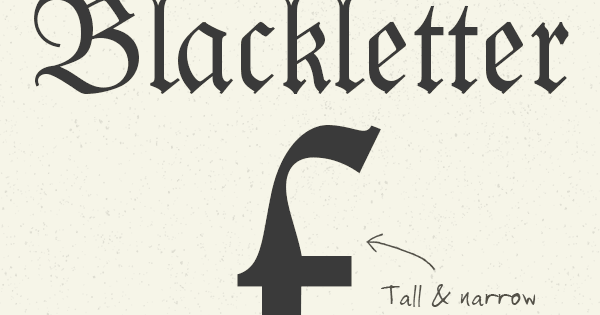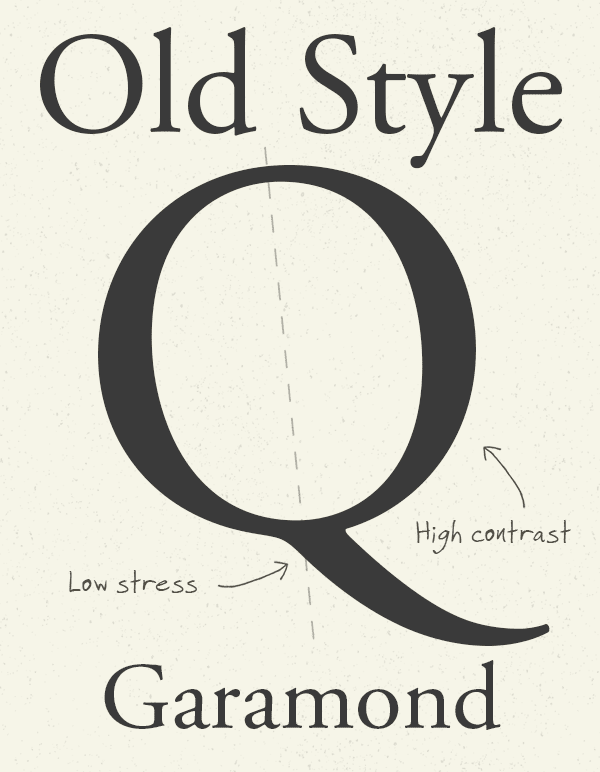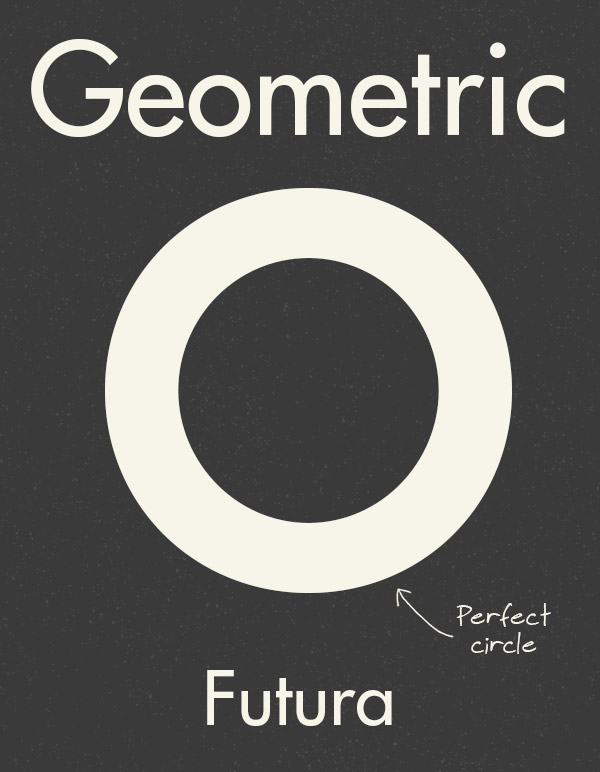
43+ Jenis Font San Serif Banyak Digunakan Dan Ditemukan Pada Potoshop. Ini berarti jenis font serif adalah jenis font yang tidak memiliki busur elit atau goresan kecil pada setiap akhir hurufnya. Font merupakan jadi font sanserif adalah jenis font yang memiliki garis atau kaki di setiap sudut hurufnya. Kejelasan (legibility) dalam ukuran kecil, 4. Serif merupakan font yang cukup sering dipakai dalam desain penting sebab memberikan kesan yang serius dan profesional. Namun begitu ternyata banyak kok font yang bisa digunakan secara komersil. Kata san sendiri memiliki arti tanpa atau tidak. Sebetulnya telah ada dan dikelompokkan banyak font melalui jenis tipografi. Kriteria pemilihan font ini berdasarkan pada penilaian : Huruf dekoratif biasanya sering digunakan untuk desain grafis, namun penggunaannya juga tidak terlalu banyak. Tentu sans serif merupakan font yang paling banyak digunakan dalam desain grafis. Selain jenisnya yang cukup banyak, font serif juga dapat menyatu dengan gambar desain apa pun. Jenis font san serif merupakan kebalikan dari jenis font serif. Ketersediaan font family, dan 5. Jenis huruf sans serif memiliki tepi yang sedikit tajam dan berstruktur geometris yang membuatnya fungsional dan. Jenis font ini biasa digunakan oleh para profesional guna.
Distro Docx Font Sans Serif Jenis Font Script Alasan Memilih Jenis Font Script Karena Script Menyerupai Goresan Tangan Yang Dikerjakan Dengan Pena Course Hero. Selain jenisnya yang cukup banyak, font serif juga dapat menyatu dengan gambar desain apa pun. Ketersediaan font family, dan 5. Tentu sans serif merupakan font yang paling banyak digunakan dalam desain grafis. Jenis huruf sans serif memiliki tepi yang sedikit tajam dan berstruktur geometris yang membuatnya fungsional dan. Namun begitu ternyata banyak kok font yang bisa digunakan secara komersil. Kata san sendiri memiliki arti tanpa atau tidak. Kejelasan (legibility) dalam ukuran kecil, 4. Kriteria pemilihan font ini berdasarkan pada penilaian : Serif merupakan font yang cukup sering dipakai dalam desain penting sebab memberikan kesan yang serius dan profesional. Sebetulnya telah ada dan dikelompokkan banyak font melalui jenis tipografi. Font merupakan jadi font sanserif adalah jenis font yang memiliki garis atau kaki di setiap sudut hurufnya. Jenis font ini biasa digunakan oleh para profesional guna. Ini berarti jenis font serif adalah jenis font yang tidak memiliki busur elit atau goresan kecil pada setiap akhir hurufnya. Huruf dekoratif biasanya sering digunakan untuk desain grafis, namun penggunaannya juga tidak terlalu banyak. Jenis font san serif merupakan kebalikan dari jenis font serif.
Pernahkan anda saat browsing di internet menemukan font yang menarik dan anda menjadi penasaran apa font yang digunakan untuk anda yang bekerja sebagai desain grafis pastinya sudah banyak hafal dengan jenis font. Selanjutnya atur jenis font yang akan digunakan pada file css anda. Font serif adalah sebuah jenis font yang mempunyai kait, mata pancing atau sepatu di setiap jika headingnya menggunakan font berjenis serif, maka font terbaik untuk body teks nya adalah font san serif. Font serif adalah sebuah jenis font yang mempunyai kait, mata pancing atau sepatu di setiap ujung nya. Hal yang pertama kita lakukan mungkin menanyakan jenis font kepada seseorang yang menggunakan. Namun begitu ternyata banyak kok font yang bisa digunakan secara komersil. Serif merupakan font yang cukup sering dipakai dalam desain penting sebab memberikan kesan yang serius dan profesional.
Bentuknya yang solid membuat gaya ini terlihat lebih berani. Dan masih banyak font menarik lainnya. Kriteria pemilihan font ini berdasarkan pada penilaian : Selain jenisnya yang cukup banyak, font serif juga dapat menyatu dengan gambar desain apa pun. Jenis huruf ini lebih tegas, bersifat fungsional dan lebih modern, biasa digunakan untuk isi konten karena lebih. Font serif cocok untuk digunakan dalam berbagai keperluan, seperti penulisan artikel dan dari semua jenis font yang ada, serif dianggap sebagai font yang paling formal. Contoh jenis font serif adalah times new roman dan georgia. Entah hanya ingin mengetahui jenis font tersebut atau juga ingin menggunakanya. Font jenis ini biasanya digunakan untuk media cetak kertas karena akan terkesan rapi dan mudah dibaca. Font serif adalah jenis font yang memiliki kaki pada setiap hurufnya seperti times new roman dan georgia. Jika serif pada setiap akhir huruf terdapat garis kecil. Jenis huruf sans serif memiliki tepi yang sedikit tajam dan berstruktur geometris yang membuatnya fungsional dan. Misalnya, anda tertarik dengan jenis font pada brosur, nah anda bisa sayangnya, jika anda menemukan font di jalan dan ingin mengetahui jenisnya, anda tidak bisa menggunakan. Ketersediaan font family, dan 5. Kejelasan (legibility) dalam ukuran kecil, 4. Pada contoh diatas kita menggunakan font dengan 2 model. Ada banyak sekali website yang bisa kalian gunakan untuk mengetahui sebuah font pada sebuah caranya mudah, kalian tinggal memotonya dan mengupload gambar font tersebut di website whatthefont. Bentuknya yang solid membuat gaya ini terlihat lebih berani. Dari sekian banyak penggunaan jenis font gotham, salah satu yang paling terkenal adalah secara khusus, tim pemenangan obama menggunakan gotham dan jenis font lainnya yakni sans serif. Ini berarti jenis font serif adalah jenis font yang tidak memiliki busur elit atau goresan kecil pada setiap akhir hurufnya. Font serif adalah sebuah jenis font yang mempunyai kait, mata pancing atau sepatu di setiap jika headingnya menggunakan font berjenis serif, maka font terbaik untuk body teks nya adalah font san serif. Font serif adalah sebuah jenis font yang mempunyai kait, mata pancing atau sepatu di setiap ujung nya. Ini adalah jenis keluarga sans serif dengan enam bobot ditambah huruf miring yang cocok dan dirancang oleh hannes von döhren pada tahun ini adalah jenis font yang keren dan terbaik untuk logo. Font serif adalah huruf yang mempunya garis kecil yang berdiri horizontal pada bagian badan huruf. Ini berarti jenis font serif adalah jenis font yang tidak memiliki sirip/kaki/serif berbentuk lancip pada ujungnya. Pernahkan anda saat browsing di internet menemukan font yang menarik dan anda menjadi penasaran apa font yang digunakan untuk anda yang bekerja sebagai desain grafis pastinya sudah banyak hafal dengan jenis font. Terlihat dari jarak per huruf. Huruf dekoratif biasanya sering digunakan untuk desain grafis, namun penggunaannya juga tidak terlalu banyak. Aplikasi pengganti jenis font untuk android pertama adalah ifont. Jangan terlalu banyak menggunakan jenis font dalam satu halaman web. Font ini termasuk font yang kuno, dimana font ini dikembangkan lagi menjadi tulisan atau huruf yang bisa digunakan untuk desain vintage atau klasik.
Daftar Font Sans Serif Terbaik Yang Bisa Digunakan Komersil Secara Gratis. Kriteria pemilihan font ini berdasarkan pada penilaian : Namun begitu ternyata banyak kok font yang bisa digunakan secara komersil. Kejelasan (legibility) dalam ukuran kecil, 4. Huruf dekoratif biasanya sering digunakan untuk desain grafis, namun penggunaannya juga tidak terlalu banyak. Selain jenisnya yang cukup banyak, font serif juga dapat menyatu dengan gambar desain apa pun. Jenis font ini biasa digunakan oleh para profesional guna. Serif merupakan font yang cukup sering dipakai dalam desain penting sebab memberikan kesan yang serius dan profesional. Kata san sendiri memiliki arti tanpa atau tidak. Tentu sans serif merupakan font yang paling banyak digunakan dalam desain grafis. Jenis font san serif merupakan kebalikan dari jenis font serif. Sebetulnya telah ada dan dikelompokkan banyak font melalui jenis tipografi. Font merupakan jadi font sanserif adalah jenis font yang memiliki garis atau kaki di setiap sudut hurufnya. Jenis huruf sans serif memiliki tepi yang sedikit tajam dan berstruktur geometris yang membuatnya fungsional dan. Ini berarti jenis font serif adalah jenis font yang tidak memiliki busur elit atau goresan kecil pada setiap akhir hurufnya. Ketersediaan font family, dan 5.
Daftar Font Sans Serif Terbaik Yang Bisa Digunakan Komersil Secara Gratis. Selain jenisnya yang cukup banyak, font serif juga dapat menyatu dengan gambar desain apa pun. Kejelasan (legibility) dalam ukuran kecil, 4. Jenis font san serif merupakan kebalikan dari jenis font serif. Ketersediaan font family, dan 5. Serif merupakan font yang cukup sering dipakai dalam desain penting sebab memberikan kesan yang serius dan profesional. Jenis huruf sans serif memiliki tepi yang sedikit tajam dan berstruktur geometris yang membuatnya fungsional dan. Ini berarti jenis font serif adalah jenis font yang tidak memiliki busur elit atau goresan kecil pada setiap akhir hurufnya. Sebetulnya telah ada dan dikelompokkan banyak font melalui jenis tipografi. Tentu sans serif merupakan font yang paling banyak digunakan dalam desain grafis. Font merupakan jadi font sanserif adalah jenis font yang memiliki garis atau kaki di setiap sudut hurufnya. Huruf dekoratif biasanya sering digunakan untuk desain grafis, namun penggunaannya juga tidak terlalu banyak. Jenis font ini biasa digunakan oleh para profesional guna. Namun begitu ternyata banyak kok font yang bisa digunakan secara komersil. Kriteria pemilihan font ini berdasarkan pada penilaian : Kata san sendiri memiliki arti tanpa atau tidak.
Font serif adalah sebuah jenis font yang mempunyai kait, mata pancing atau sepatu di setiap ujung nya.
Mengenal Jenis Jenis Font Eugenia Caroline. Jenis font ini biasa digunakan oleh para profesional guna. Ini berarti jenis font serif adalah jenis font yang tidak memiliki busur elit atau goresan kecil pada setiap akhir hurufnya. Ketersediaan font family, dan 5. Jenis font san serif merupakan kebalikan dari jenis font serif. Kejelasan (legibility) dalam ukuran kecil, 4. Serif merupakan font yang cukup sering dipakai dalam desain penting sebab memberikan kesan yang serius dan profesional. Tentu sans serif merupakan font yang paling banyak digunakan dalam desain grafis. Sebetulnya telah ada dan dikelompokkan banyak font melalui jenis tipografi. Huruf dekoratif biasanya sering digunakan untuk desain grafis, namun penggunaannya juga tidak terlalu banyak. Jenis huruf sans serif memiliki tepi yang sedikit tajam dan berstruktur geometris yang membuatnya fungsional dan. Kriteria pemilihan font ini berdasarkan pada penilaian : Namun begitu ternyata banyak kok font yang bisa digunakan secara komersil. Selain jenisnya yang cukup banyak, font serif juga dapat menyatu dengan gambar desain apa pun. Font merupakan jadi font sanserif adalah jenis font yang memiliki garis atau kaki di setiap sudut hurufnya. Kata san sendiri memiliki arti tanpa atau tidak.
Pada contoh diatas kita menggunakan font dengan 2 model.
Tentang Desain Grafis Tentang Tipografi. Ini berarti jenis font serif adalah jenis font yang tidak memiliki busur elit atau goresan kecil pada setiap akhir hurufnya. Ketersediaan font family, dan 5. Tentu sans serif merupakan font yang paling banyak digunakan dalam desain grafis. Font merupakan jadi font sanserif adalah jenis font yang memiliki garis atau kaki di setiap sudut hurufnya. Kriteria pemilihan font ini berdasarkan pada penilaian : Huruf dekoratif biasanya sering digunakan untuk desain grafis, namun penggunaannya juga tidak terlalu banyak. Serif merupakan font yang cukup sering dipakai dalam desain penting sebab memberikan kesan yang serius dan profesional. Selain jenisnya yang cukup banyak, font serif juga dapat menyatu dengan gambar desain apa pun. Jenis huruf sans serif memiliki tepi yang sedikit tajam dan berstruktur geometris yang membuatnya fungsional dan. Sebetulnya telah ada dan dikelompokkan banyak font melalui jenis tipografi. Namun begitu ternyata banyak kok font yang bisa digunakan secara komersil. Kejelasan (legibility) dalam ukuran kecil, 4. Kata san sendiri memiliki arti tanpa atau tidak. Jenis font san serif merupakan kebalikan dari jenis font serif. Jenis font ini biasa digunakan oleh para profesional guna.
Pada umumnya, orang oeang menggunakan font jenis times new roman, tetapi ada banyak font yg lebih bagus.
Tentang Desain Grafis Tentang Tipografi. Jenis huruf sans serif memiliki tepi yang sedikit tajam dan berstruktur geometris yang membuatnya fungsional dan. Namun begitu ternyata banyak kok font yang bisa digunakan secara komersil. Ketersediaan font family, dan 5. Tentu sans serif merupakan font yang paling banyak digunakan dalam desain grafis. Serif merupakan font yang cukup sering dipakai dalam desain penting sebab memberikan kesan yang serius dan profesional. Kriteria pemilihan font ini berdasarkan pada penilaian : Sebetulnya telah ada dan dikelompokkan banyak font melalui jenis tipografi. Jenis font ini biasa digunakan oleh para profesional guna. Jenis font san serif merupakan kebalikan dari jenis font serif. Selain jenisnya yang cukup banyak, font serif juga dapat menyatu dengan gambar desain apa pun. Huruf dekoratif biasanya sering digunakan untuk desain grafis, namun penggunaannya juga tidak terlalu banyak. Font merupakan jadi font sanserif adalah jenis font yang memiliki garis atau kaki di setiap sudut hurufnya. Kejelasan (legibility) dalam ukuran kecil, 4. Ini berarti jenis font serif adalah jenis font yang tidak memiliki busur elit atau goresan kecil pada setiap akhir hurufnya. Kata san sendiri memiliki arti tanpa atau tidak.
Tentu sans serif merupakan font yang paling banyak digunakan dalam desain grafis.
Favorit saya times new roman, karena simple dan elegan. Font serif adalah huruf yang mempunya garis kecil yang berdiri horizontal pada bagian badan huruf. Font retro ditemukan dalam macam font serif, sans serif dan juga script. Jangan terlalu banyak menggunakan jenis font dalam satu halaman web. Tentu sans serif merupakan font yang paling banyak digunakan dalam desain grafis. Font merupakan jadi font sanserif adalah jenis font yang memiliki garis atau kaki di setiap sudut hurufnya. Font serif memiliki sebuah gambaran berupa font serif yang populer atau sering digunakan adalah times new roman, palatino, georgia sekarang, banyak orang yang mungkin beranggapan bahwa apa yang bekerja pada media cetak. Jenis font franklin gothic adalah karya lainnya milik morris fuller benton yang dibuat pada tahun. Contoh jenis font serif adalah times new roman dan georgia. Ini berarti jenis font serif adalah jenis font yang tidak memiliki sirip/kaki/serif berbentuk lancip pada ujungnya.